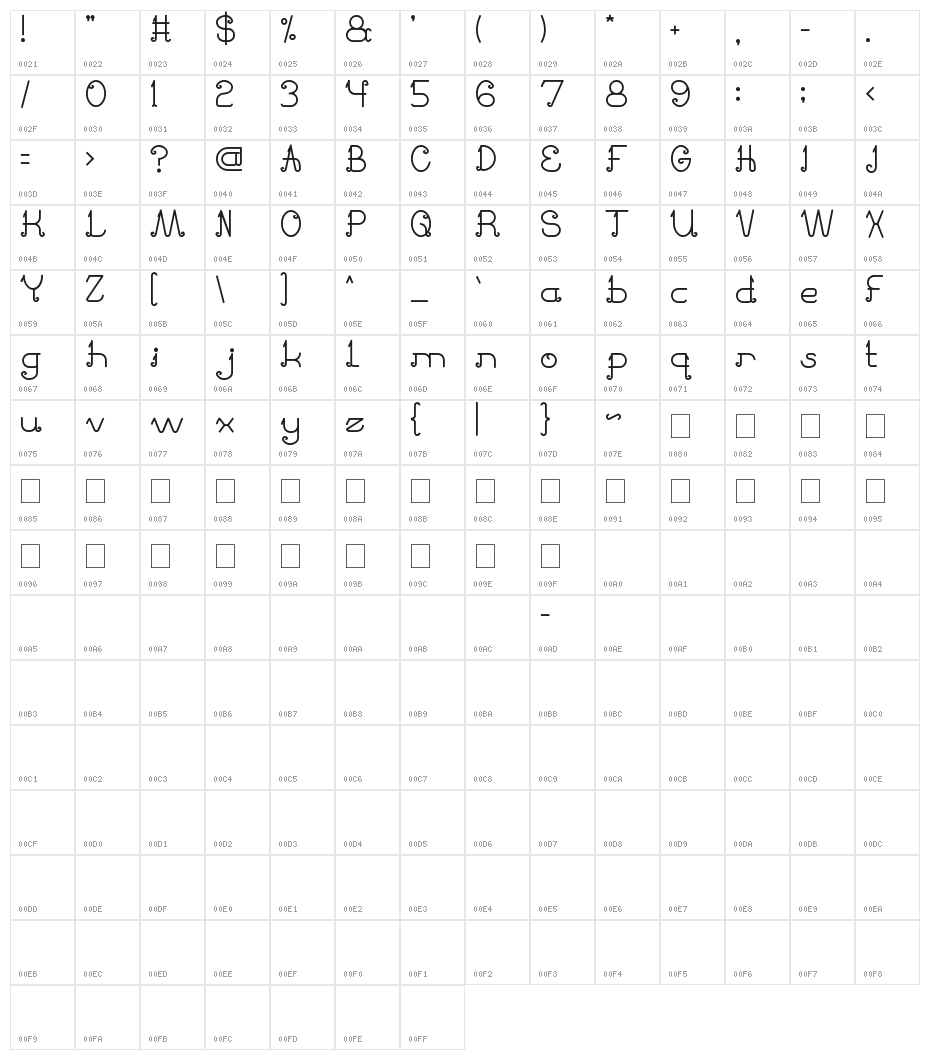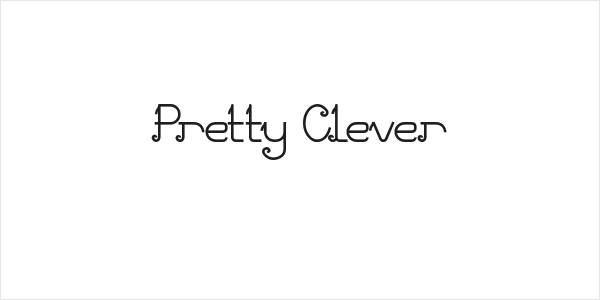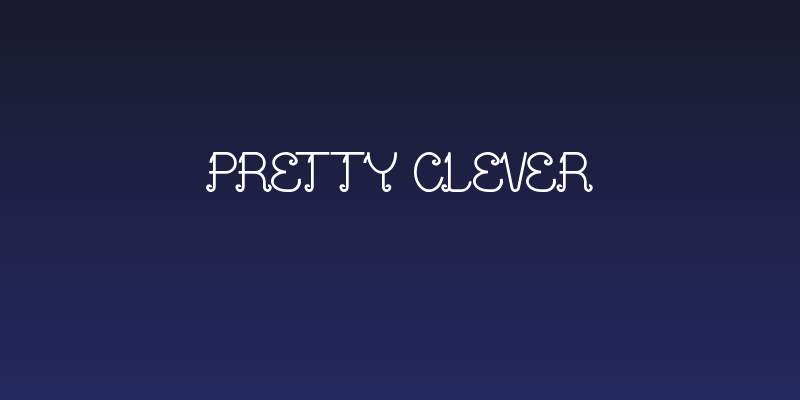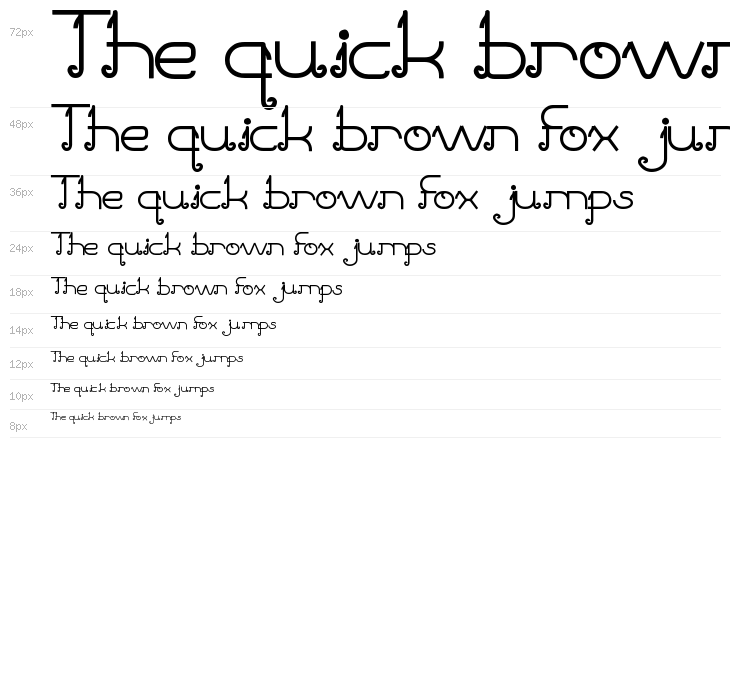
Pretty Clever Font
| Anwendungsfall | Headlines, Logos, Invitations |
| Vorgeschlagene Projekte | Ideal for invitations, greeting cards, children's books, and playful branding projects. |